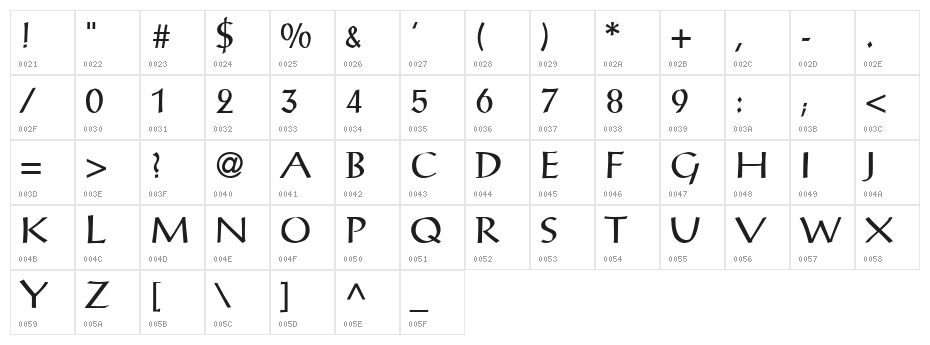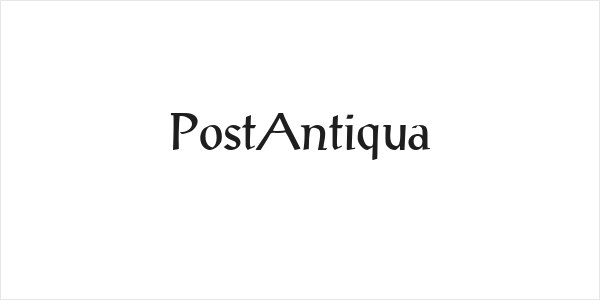
PostAntiqua Font
✎ Script
| Categorías | Script |
| Estilo general | Classic |
| Caso de uso | Headlines, Body text, Logos |
| Proyectos propuestos | Ideal for editorial design, book covers, formal invitations, and branding projects that require a classic and elegant touch. |